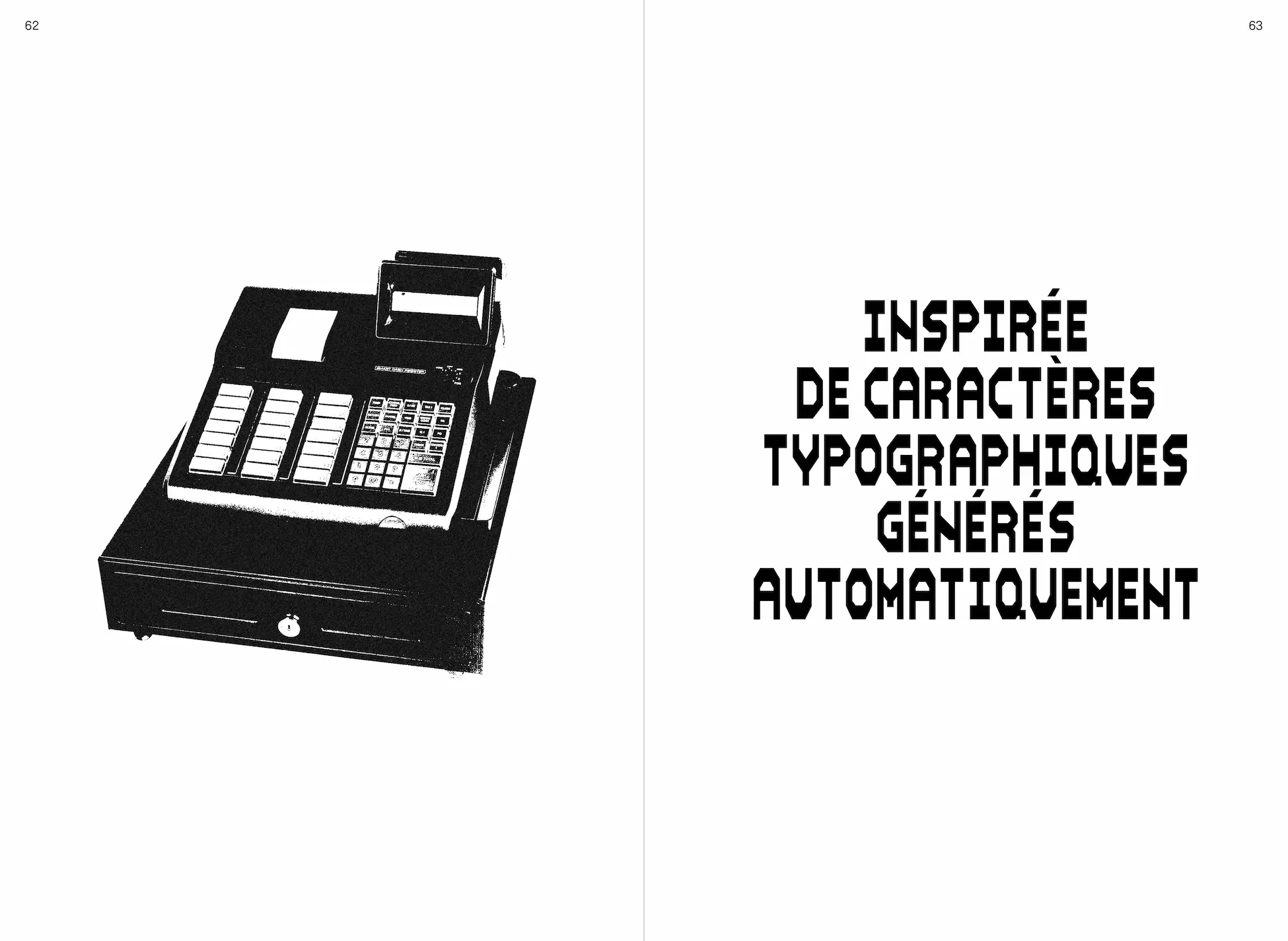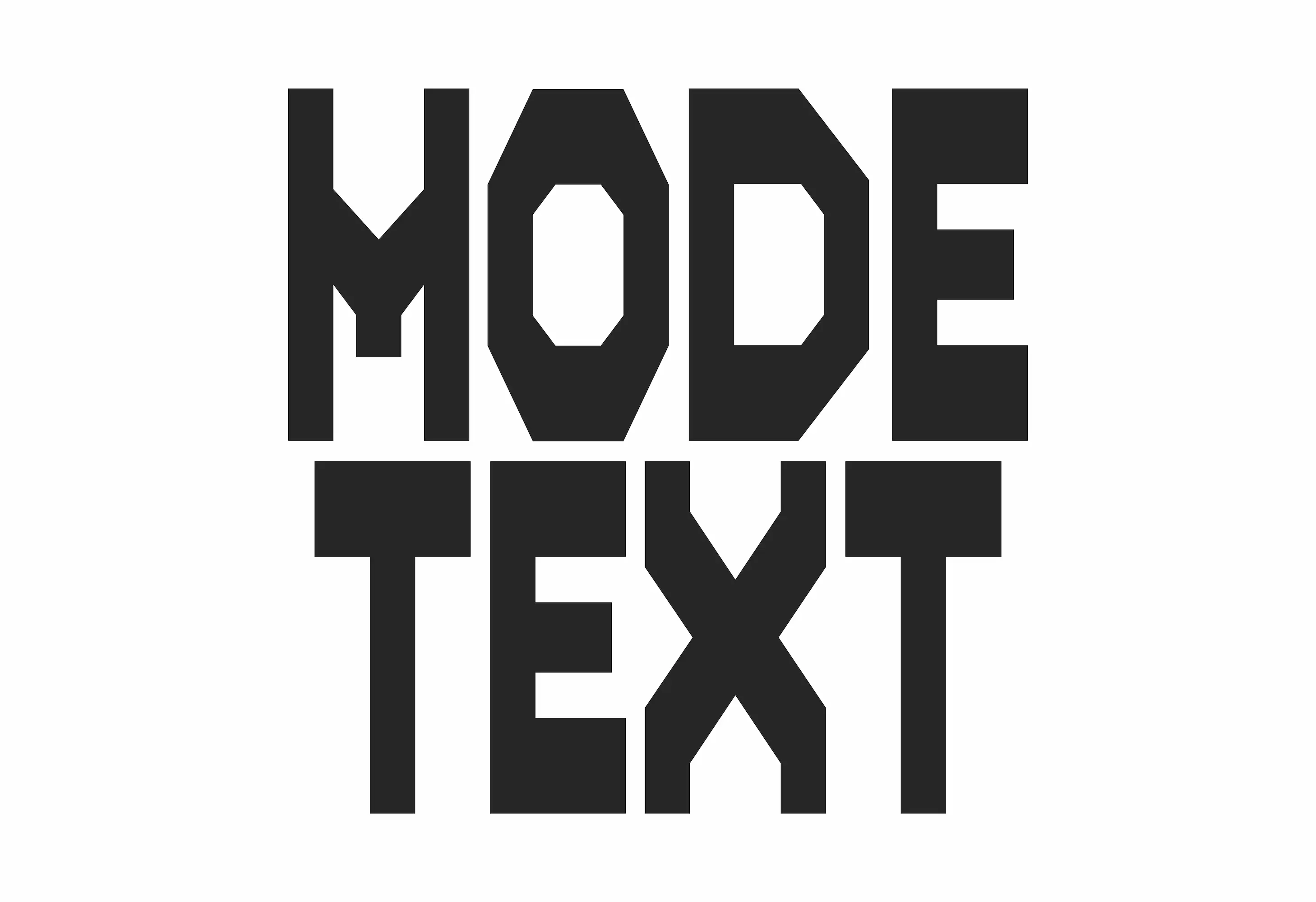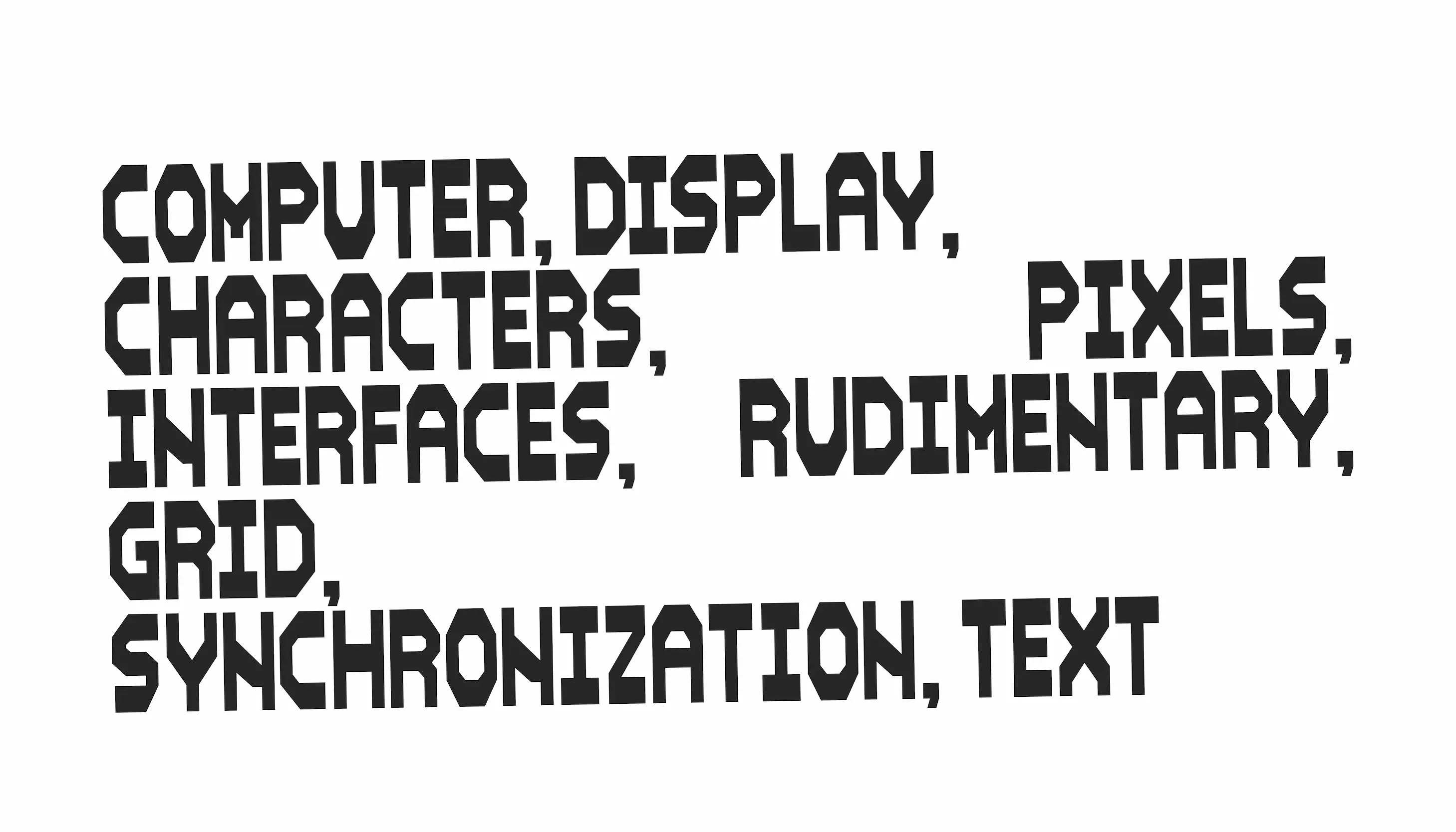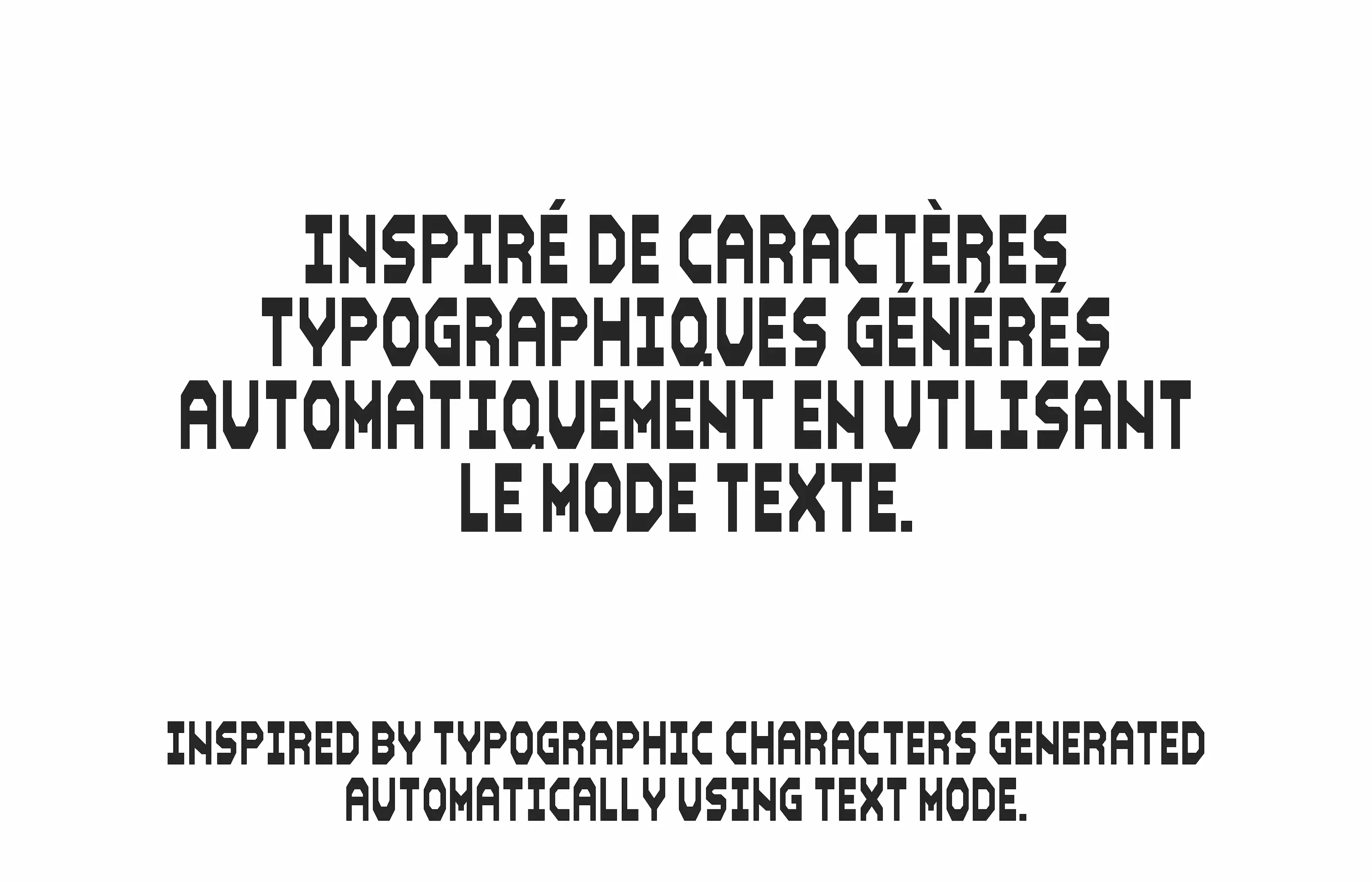
MODE TEXT
MODE TEXT est une police de caractères display qui rend hommage aux premières typographies numériques générées automatiquement. S’inspirant des premières expérimentations typographiques des débuts de l’informatique, elle réinterprète cette esthétique en introduisant des formes contrastées, apportant ainsi une touche contemporaine et un regard nouveau sur les polices de caractères souvent négligées dans les documents quotidiens.